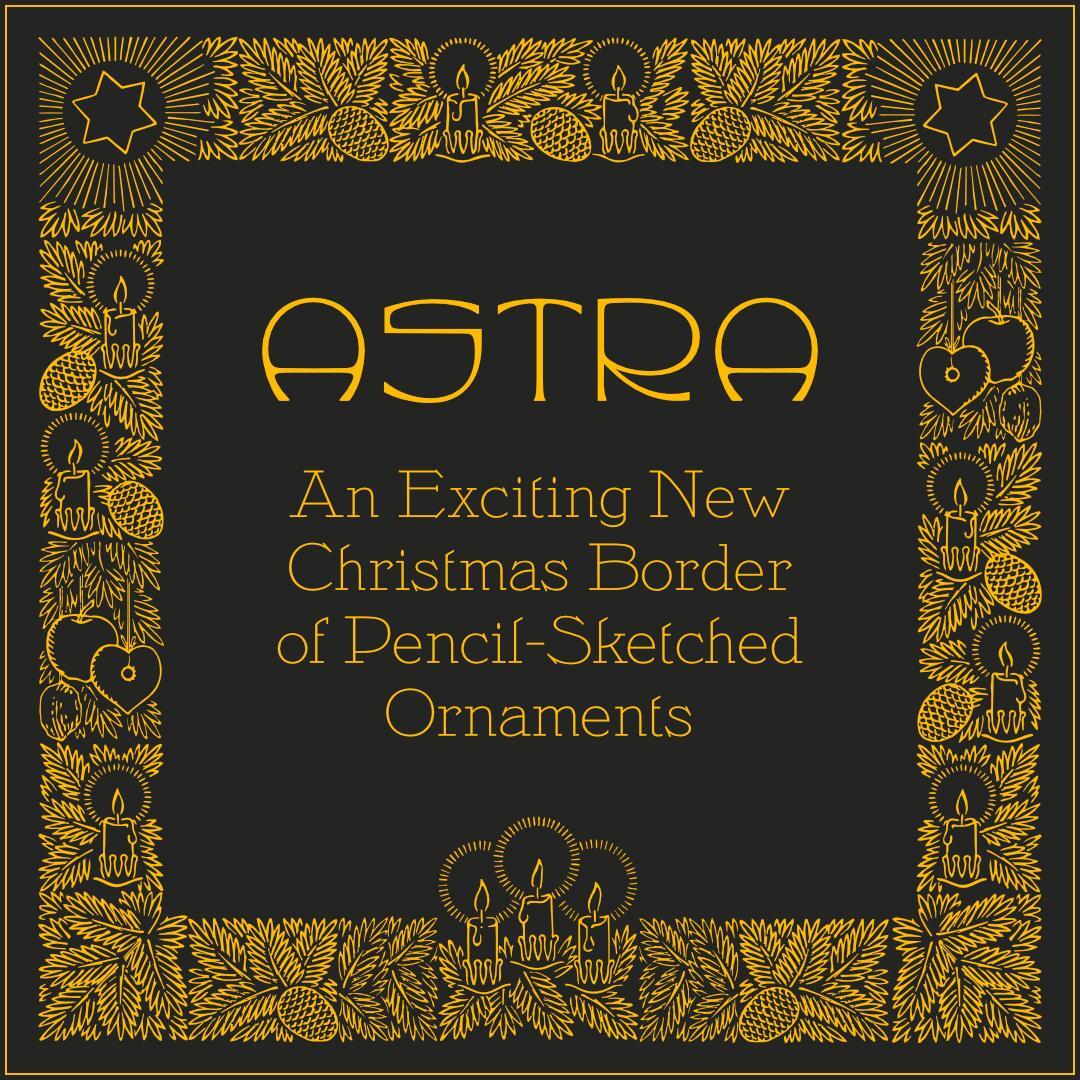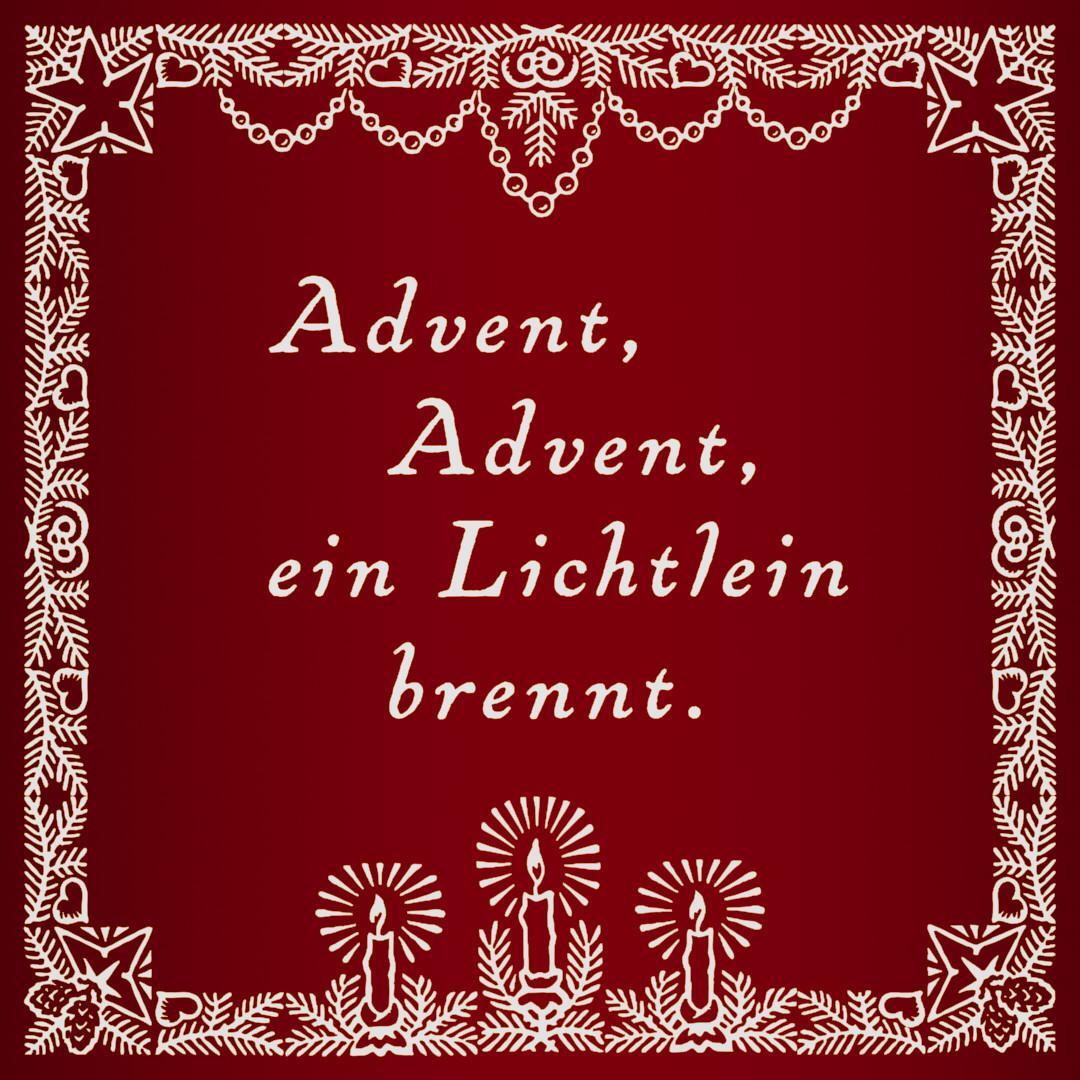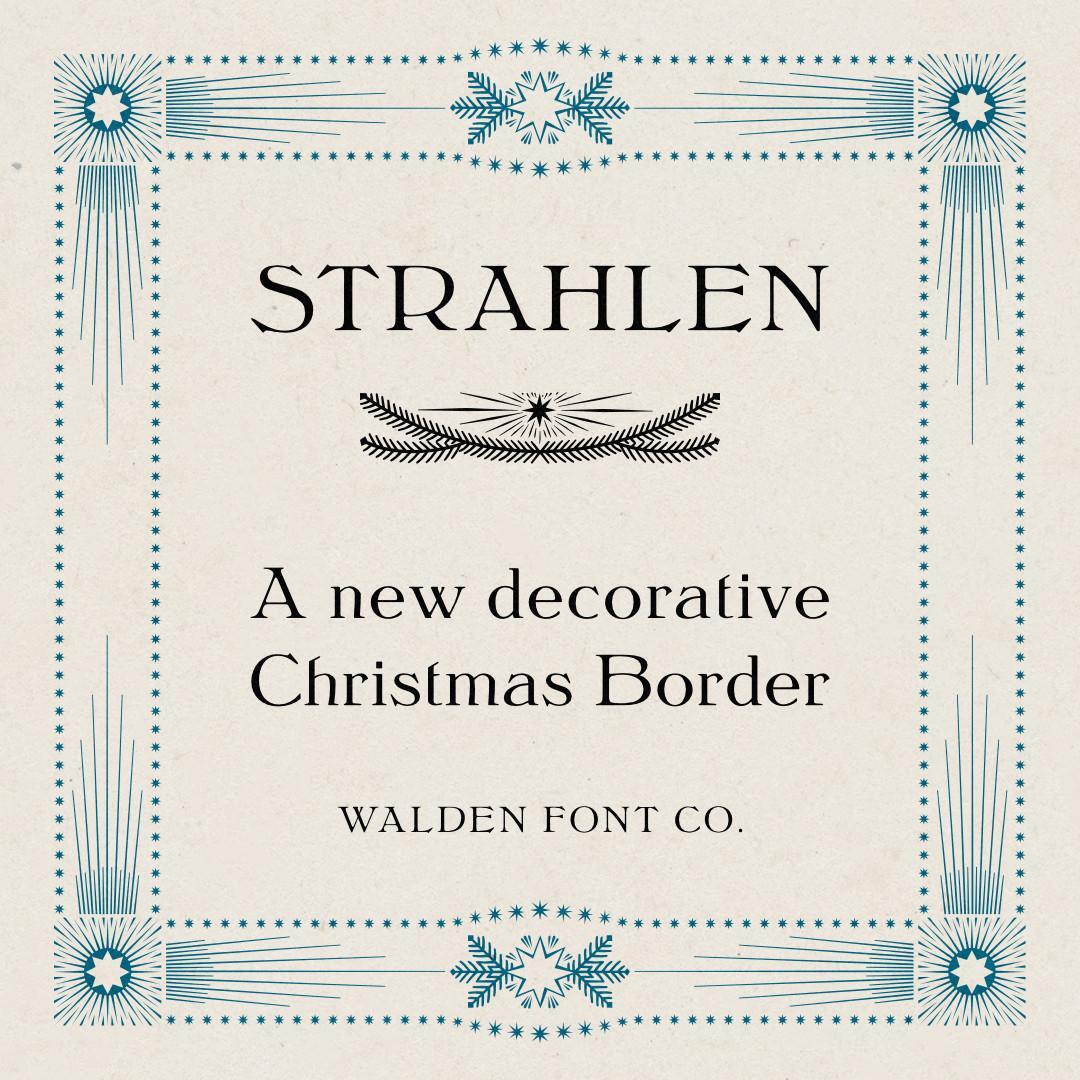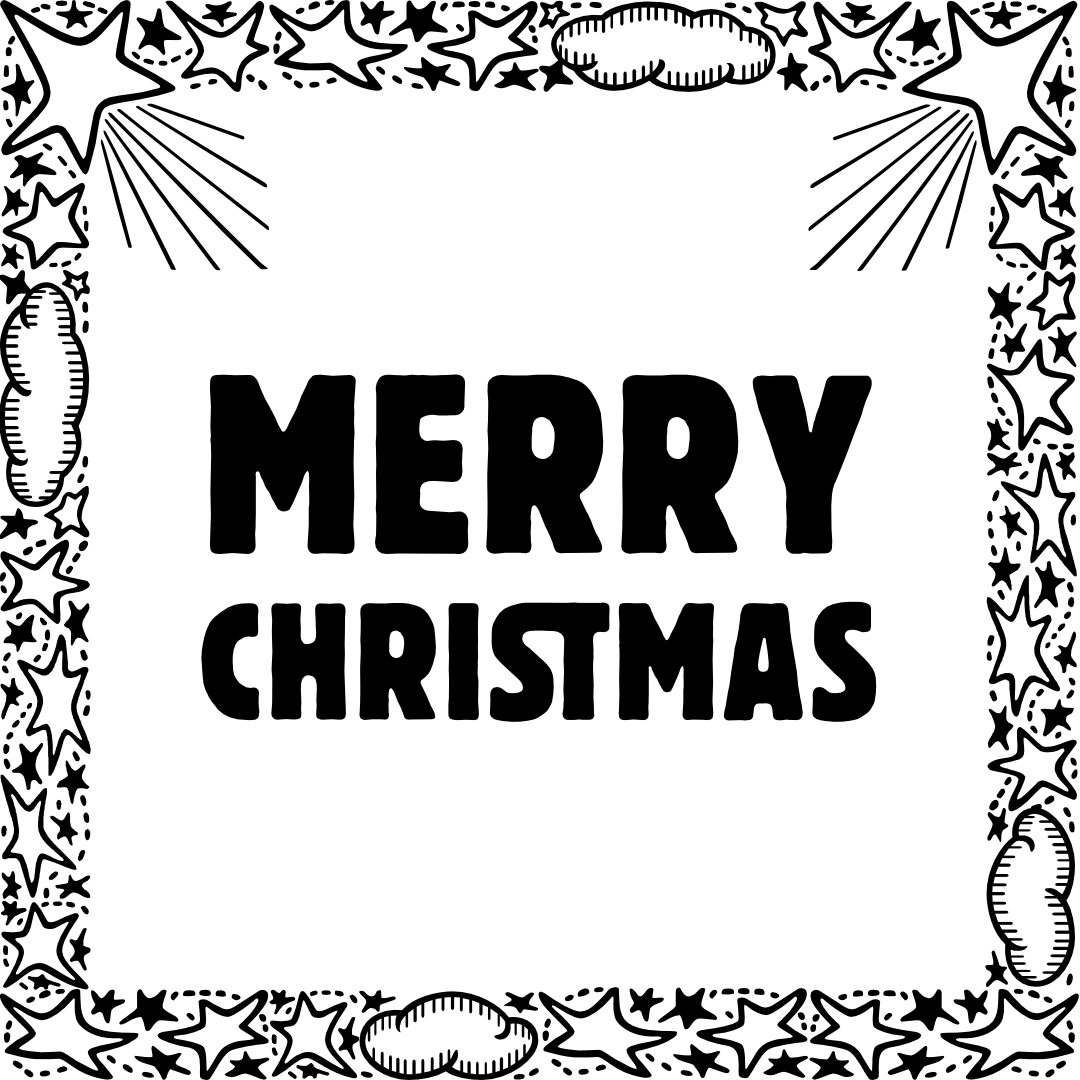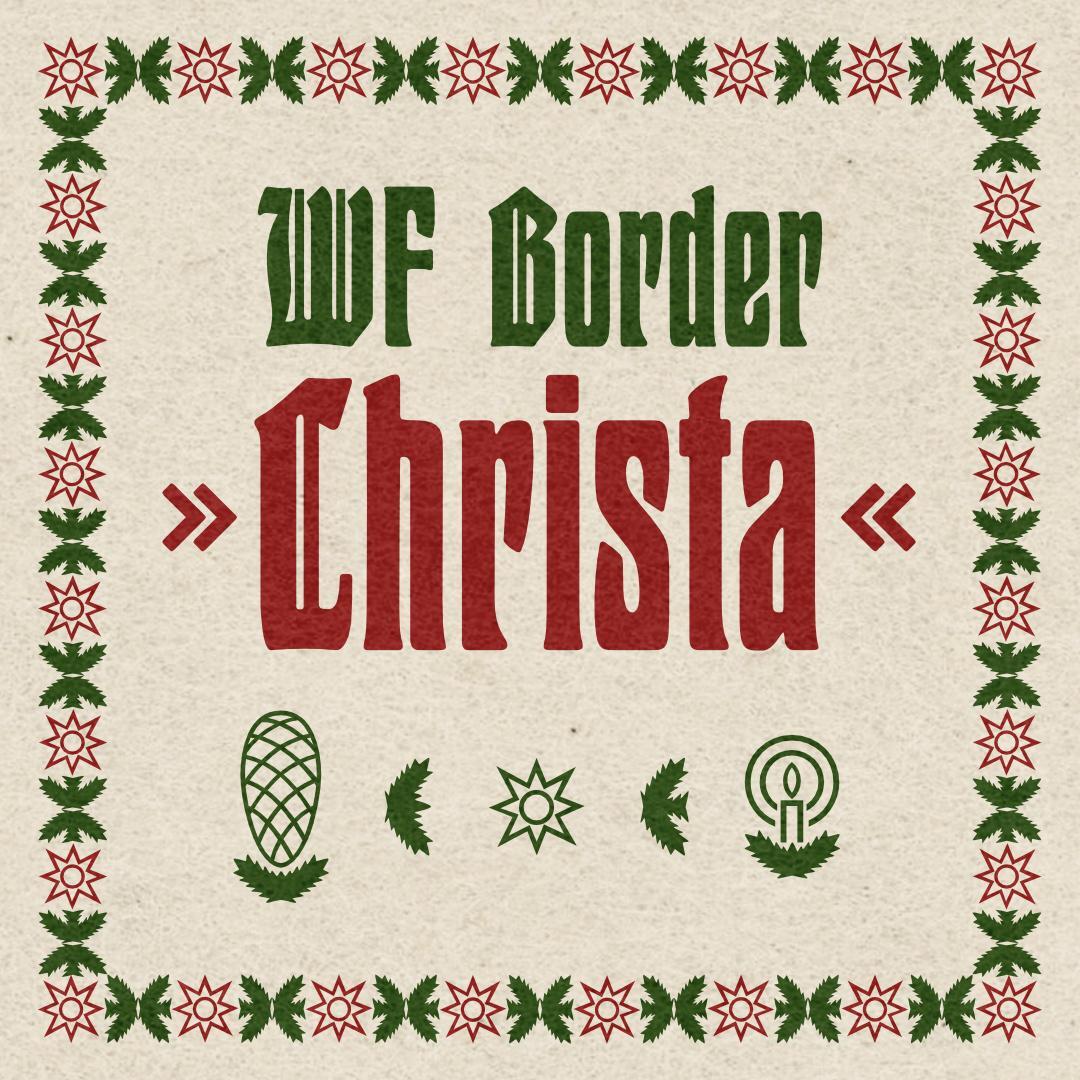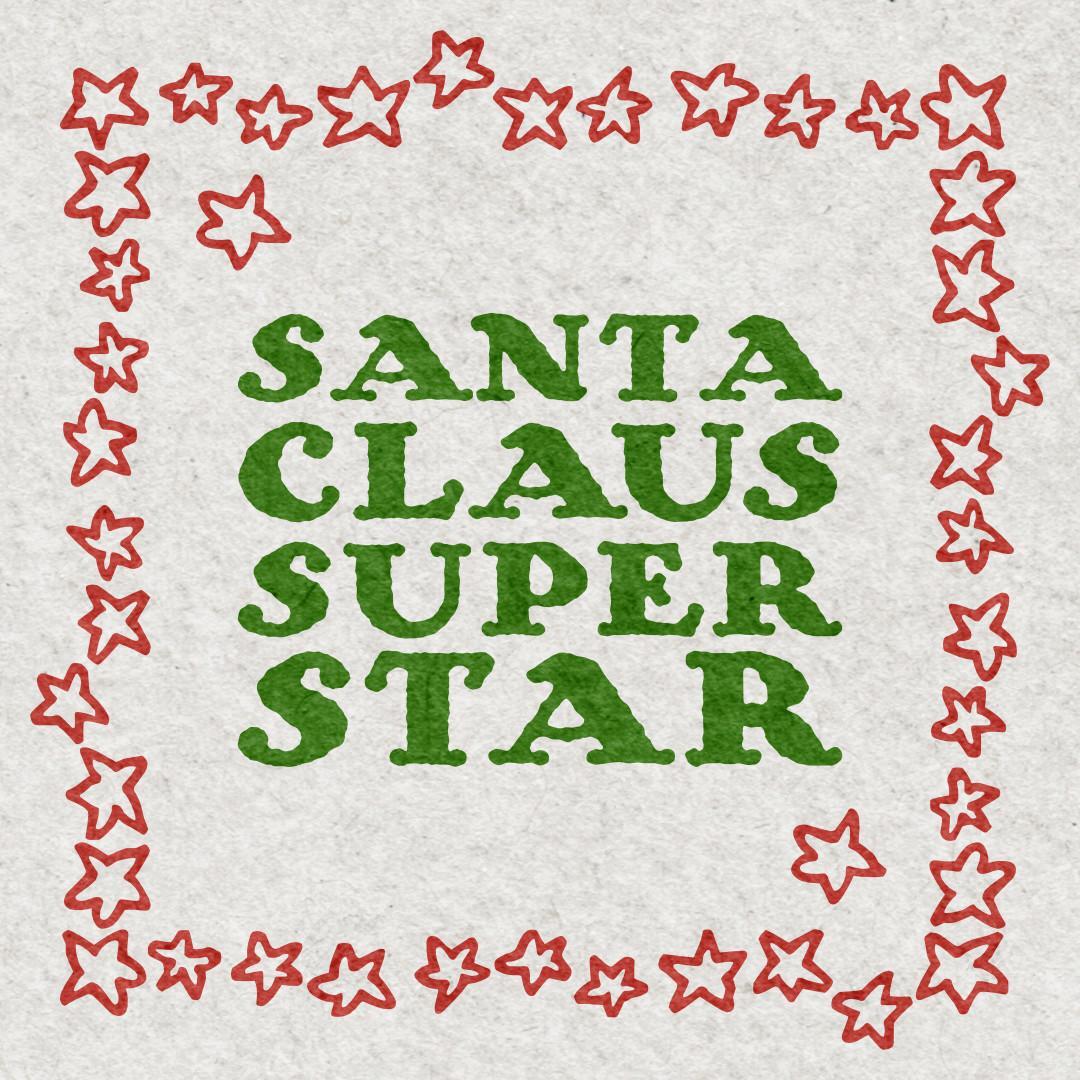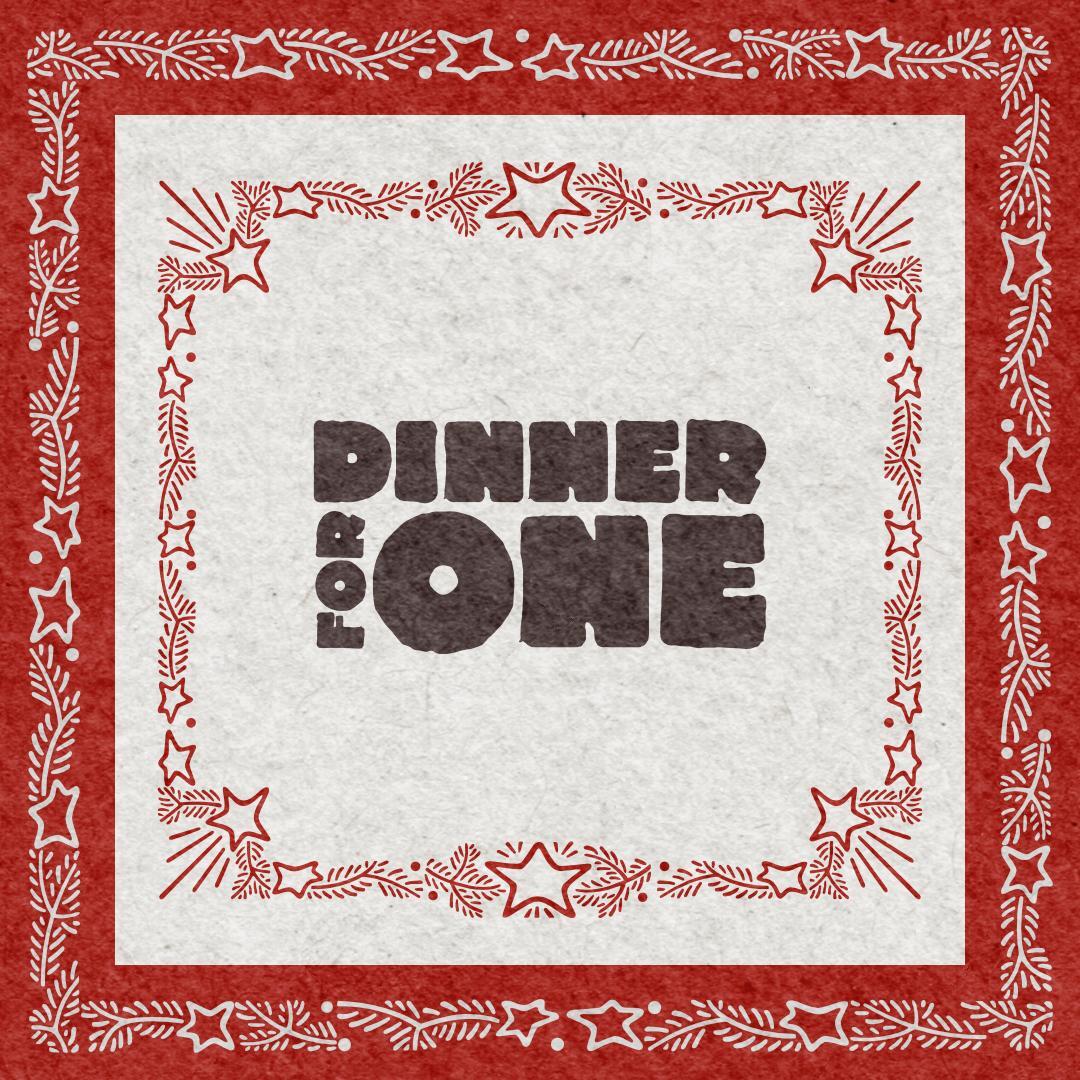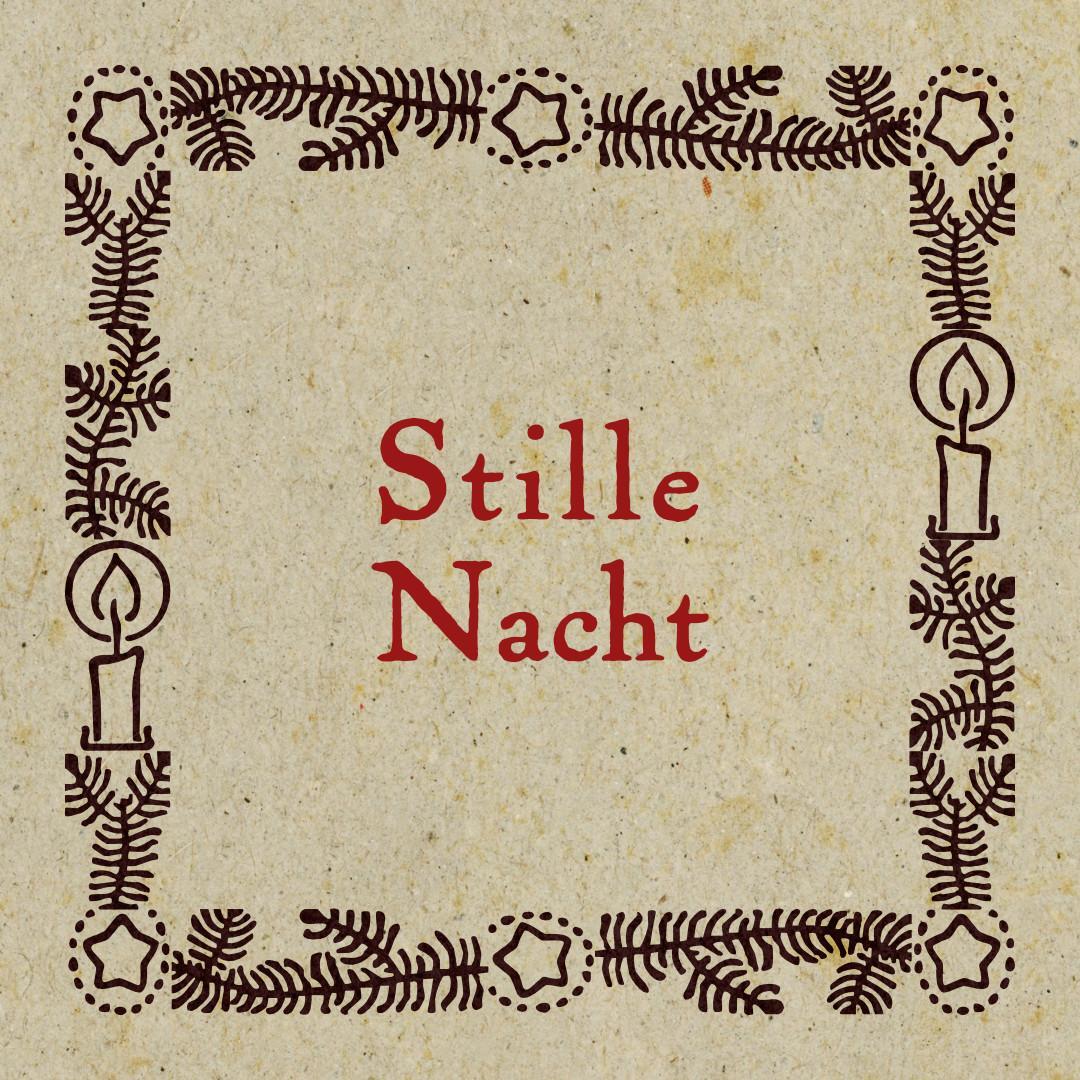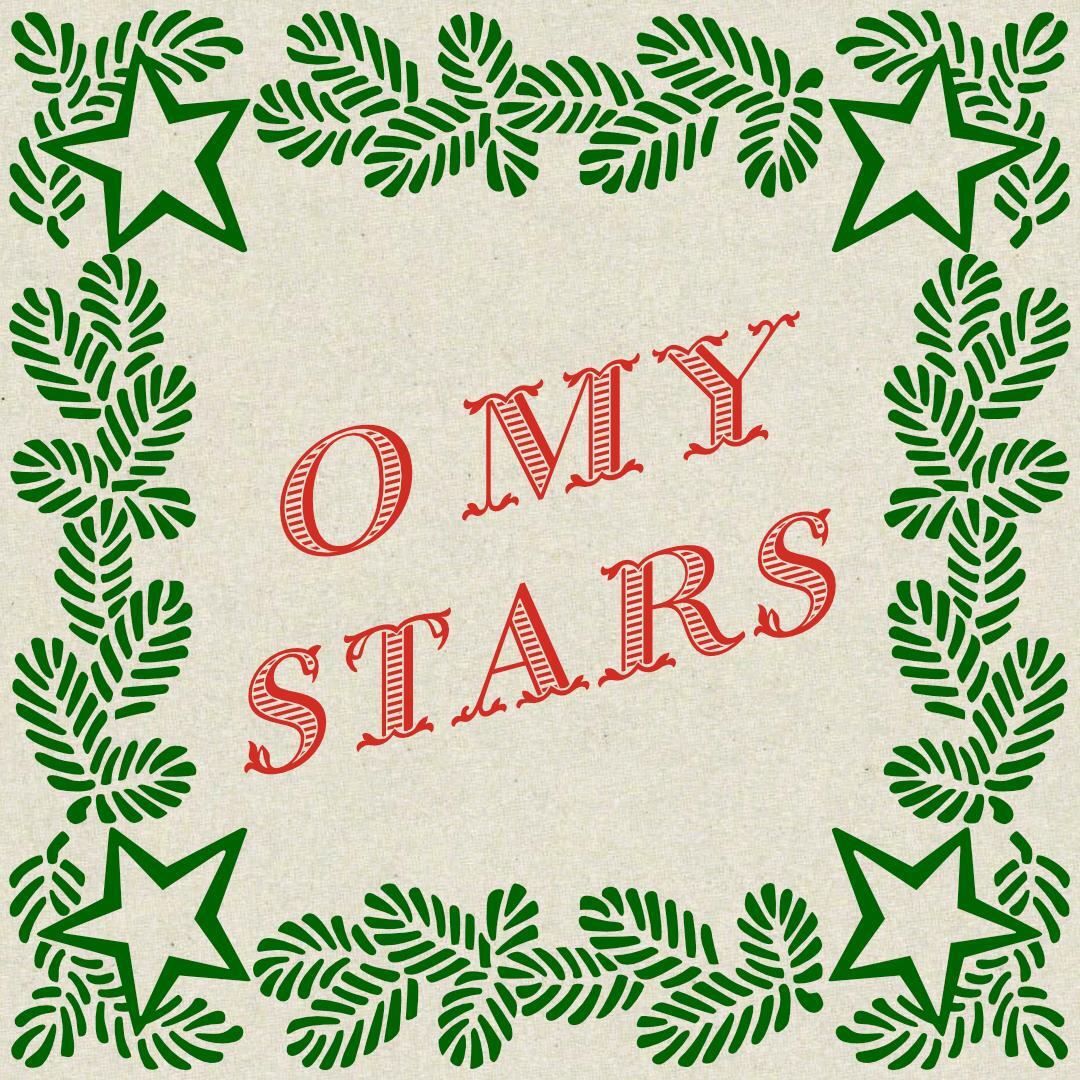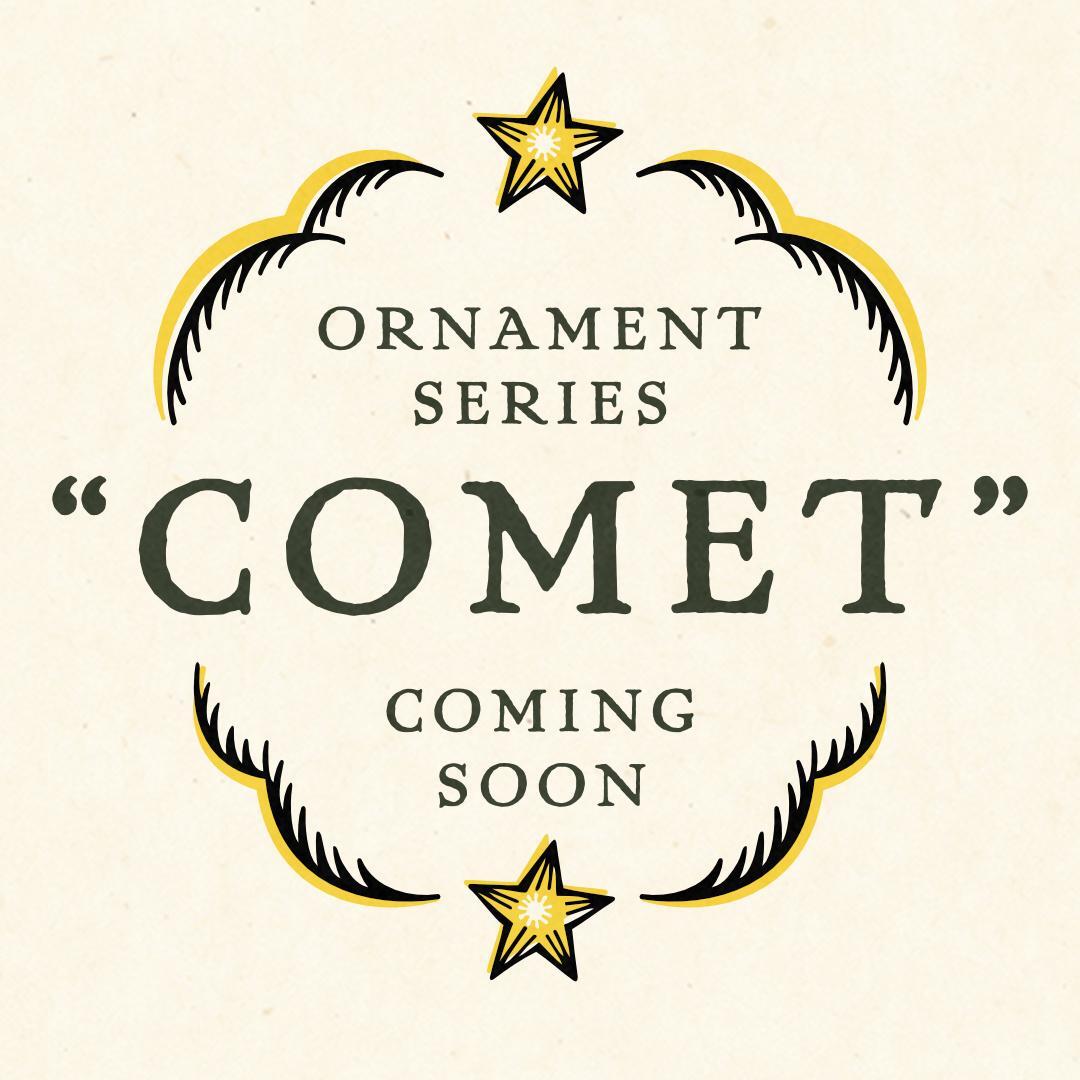
Weihnachtliches Allerlei
Viel habt Ihr in letzter Zeit nicht von mir gehört. Ich stecke im Moment bis über die Ohren in Arbeit, und nicht nur mit dem Weihnachtsprojekt. Es gibt aber ordentlich Fortschritt zu zeigen. Hier seht Ihr dreizehn weitere Einfassungen, die ich in den letzten Monaten digitalisiert habe. Sie sind alle in den 1920ern bei Brüder Butter erschienen.  (drauf klicken macht die Bilder größer)